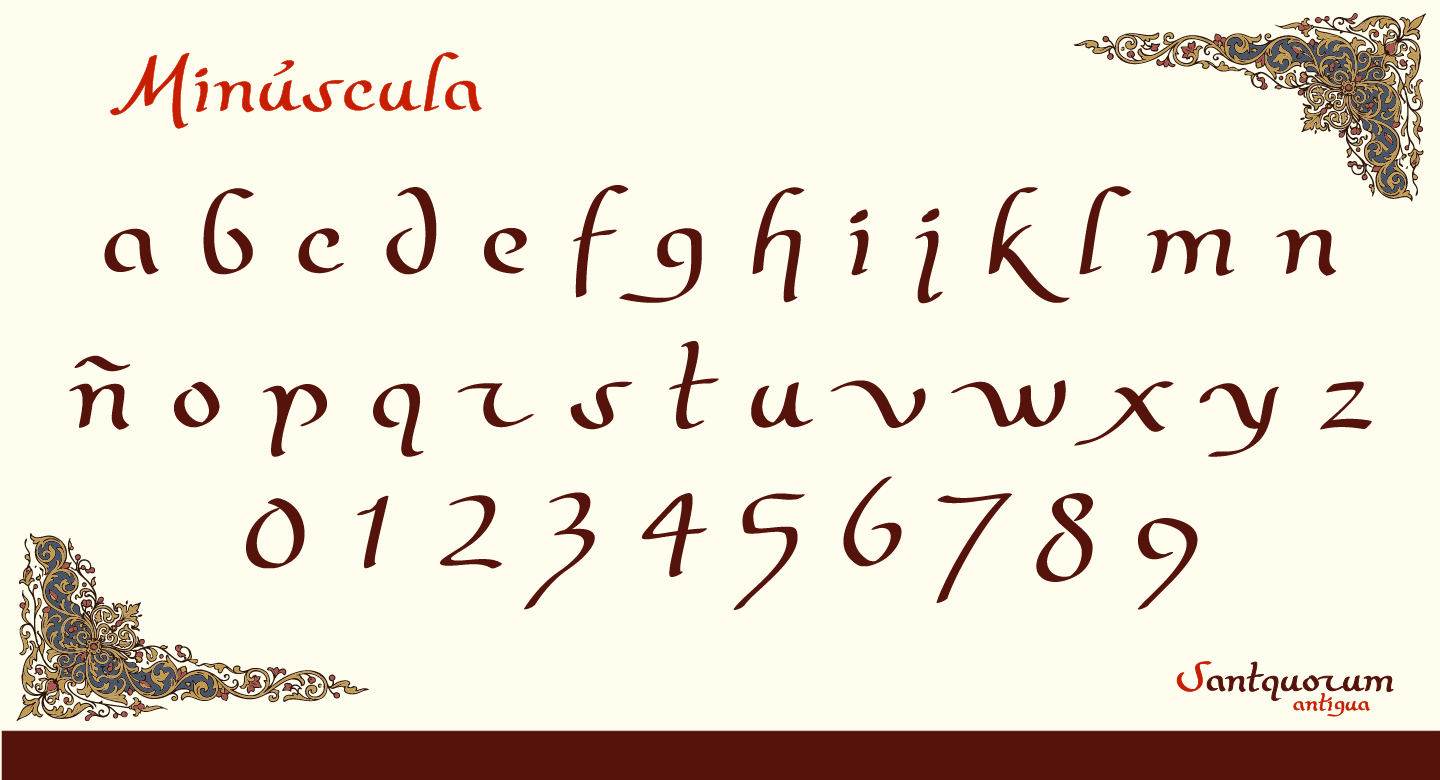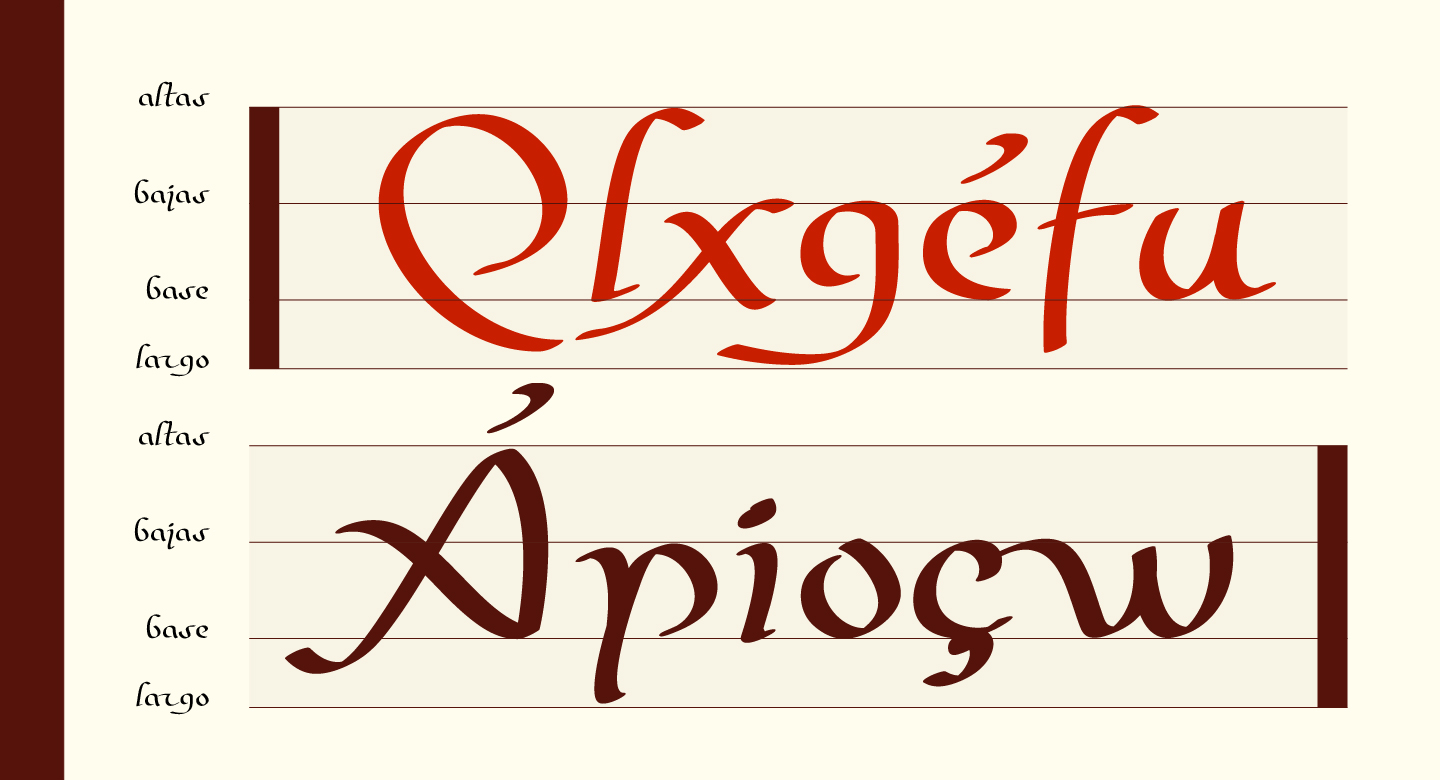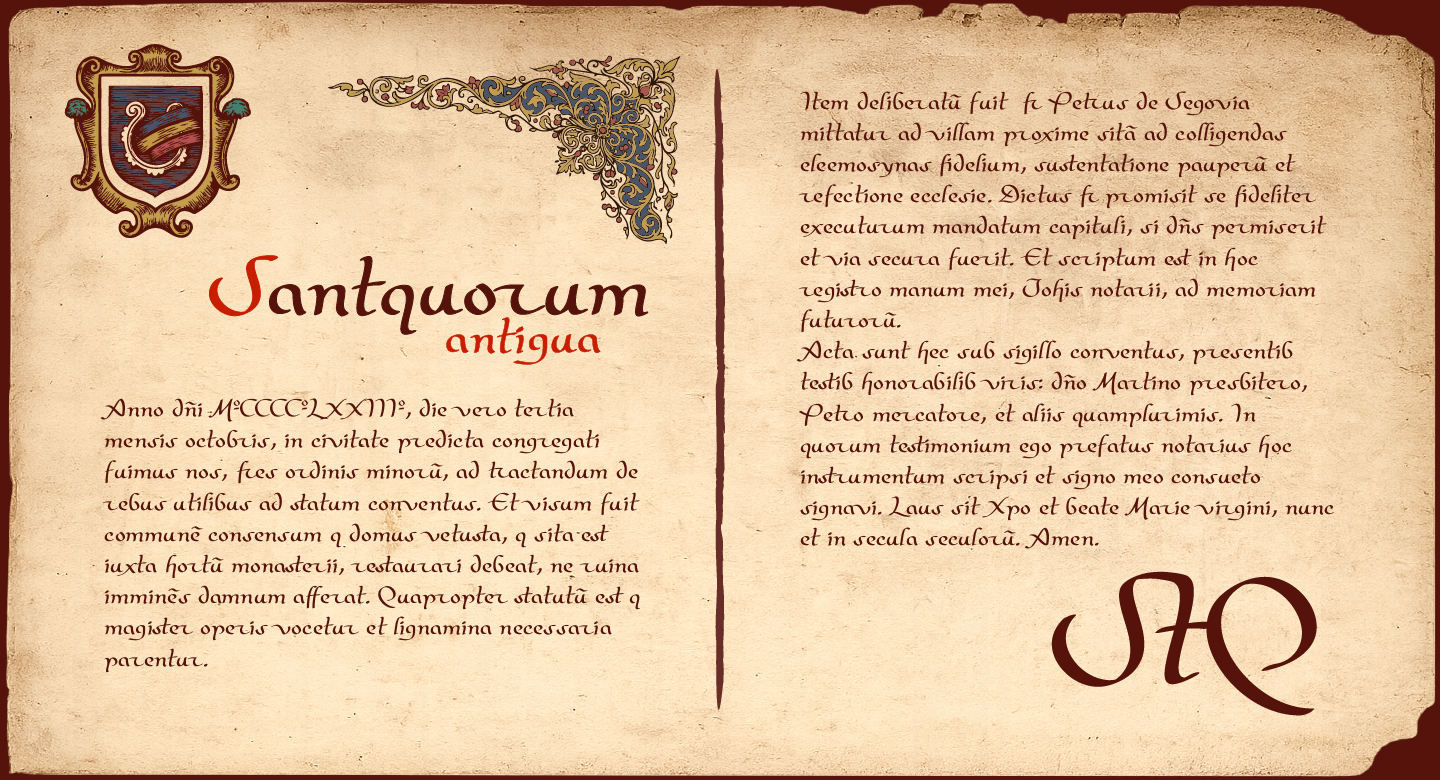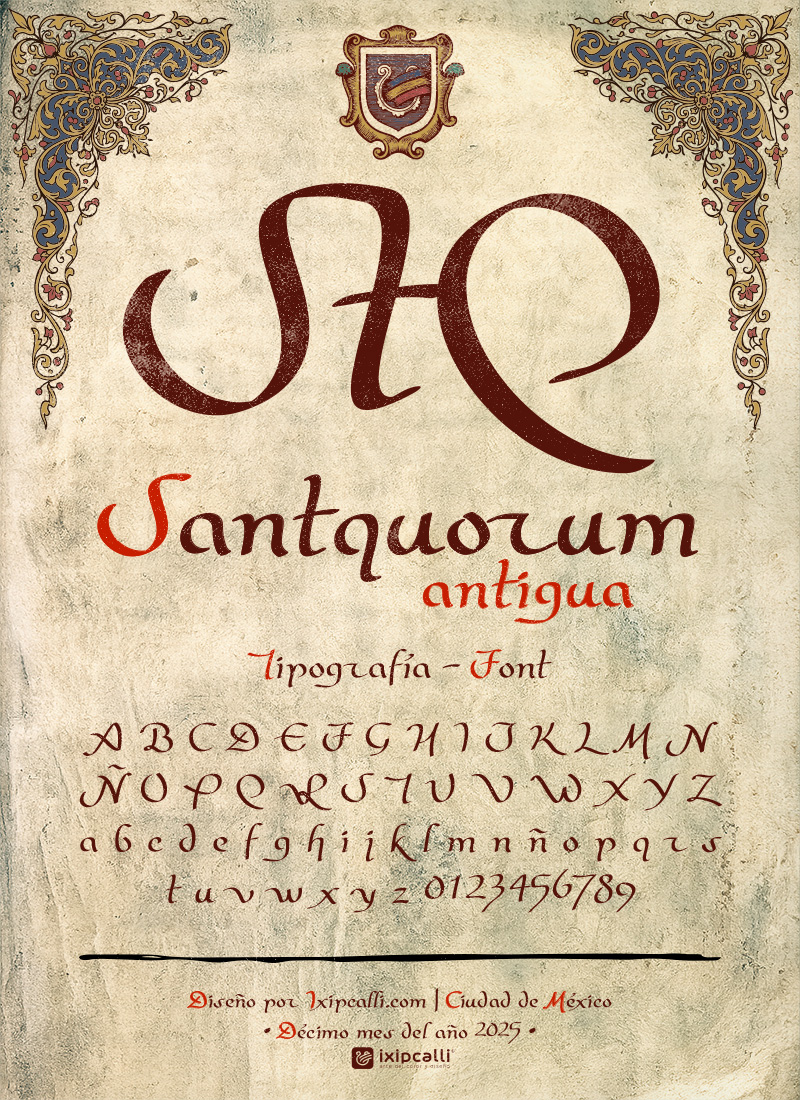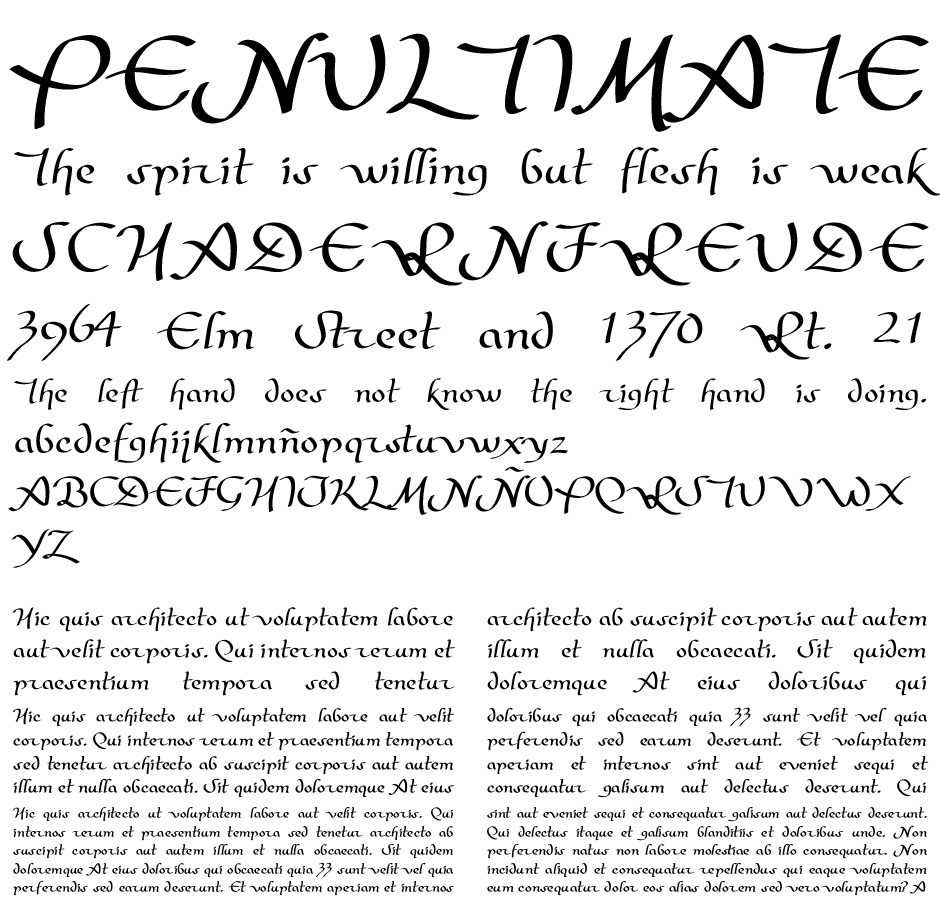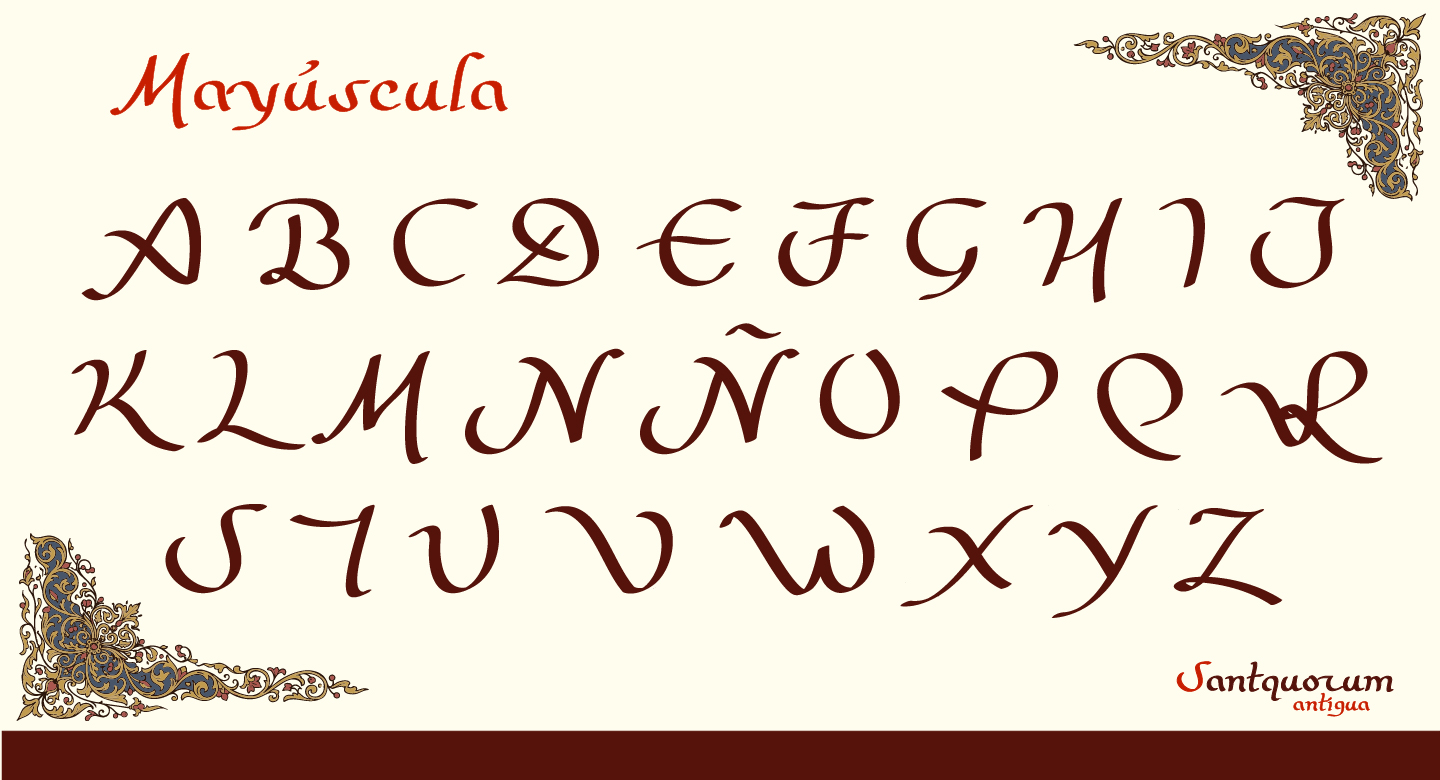
santquorum antigua
(2025) - Santquorum Antigua es una tipografía de estilo paleográfica medieval en manuscrita de documentos históricos de los siglos XIV al XVI. Su nombre significa “Santa Asamblea”, pertenenciente a la familia tipográfica del mismo nombre compuesta por cuatro evoluciones estilísticas que recorren un desarrollo conceptual, desde una forma antigua hasta una versión sans serif contemporánea.
Esta variante incorpora ligaduras y abreviaturas características de la escritura de la época, reforzando su autenticidad histórica. Su construcción formal está pensada para evocar la estética de los textos medievales sin sacrificar claridad visual.
Es adecuada para proyectos que buscan recrear la apariencia de documentos históricos, ediciones facsimilares, publicaciones académicas o identidades visuales con una fuerte referencia patrimonial. La estructura de sus trazos favorece una lectura fluida, permitiendo que la tipografía funcione también dentro de composiciones editoriales contemporáneas con un carácter neoclásico.